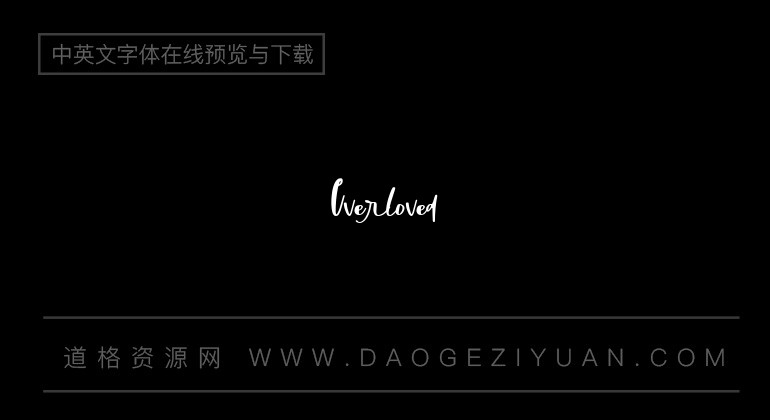
Everloved
Everloved 字体是一款简约、可爱的手写字体,由英国设计师瑞安·拉米尔创作。它具有一种温暖的、粗犷的手写体风格,适合用于制作浪漫的海报、插图、卡片等设计作品。Everloved 字体包含多个字符,可以满足不同的设计需求。它的特点是字体的每个字母都有一种独特的手写风格,可以增添设计作品的温暖气息。
Everloved是一款非常不错的手写艺术字体,具有很好的视觉感,适合于文化类的宣传设计、商业类品牌的广告和产品包装设计以及个性化文字排版等较多场景。